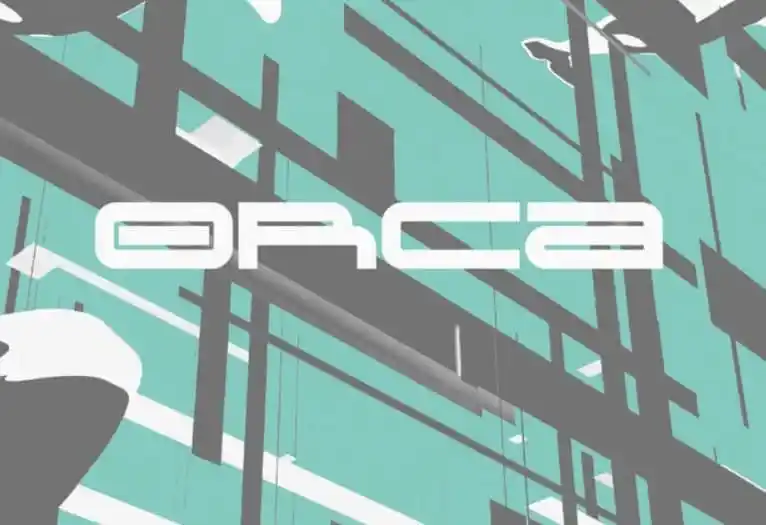
A Orca Display Font é uma elegante escolha para criar design visual impactantes e versáteis, ideal para marcas de negócios, logotipos ou apresentações de slides. Desenvolvida pelo designer Ross Lowder, essa sans serif se destaca pela sua disposição larga e presença forte. Suas linhas grossas têm contraste elevado, procurando um equilíbrio delicado entre legibilidade e abstração, com proporções extremas, formas únicas, espaçamento kerning densoado e uma aparência geral robusta e pesada. Esta fonte é perfeita para criar marcas de negócios atemporais ou levar um toque inovador aos seus projetos gráficos. A Orca Display oferece uma linguagem clara que, ao mesmo tempo, tem o poder de ser impactante e não perder seu equilíbrio entre a simplicidade e a complexidade. Ela é perfeitamente adaptável para vários ambientes, do digital aos prints tradicionais, permitindo-lhe criar design visual único e memorável.